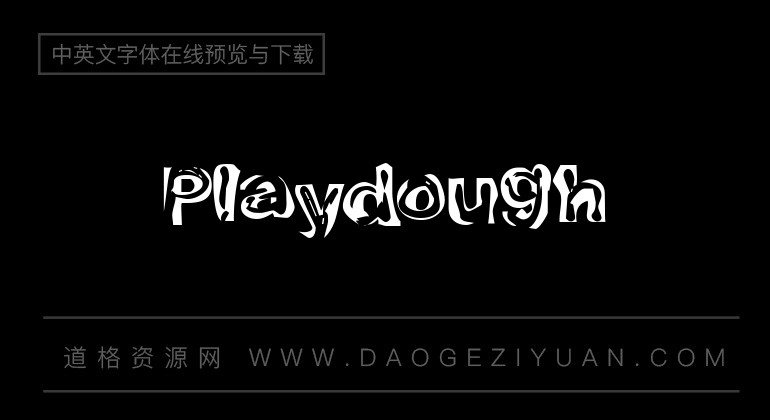
Playdough 是一款极具特色的手写字体,它的外形充满了活力,充满了童趣,适合用于卡片、海报、T恤等各种设计中。它的设计灵感来自于孩子们玩面团时的书写,它的字体特点是毛笔书写的外观,具有极大的艺术感,同时又不失清晰度。内容介绍
Playdough是一款非常不错的手写艺术字体,具有很好的视觉感,适合于文化类的宣传设计、商业类品牌的广告和产品包装设计以及个性化文字排版等较多场景。